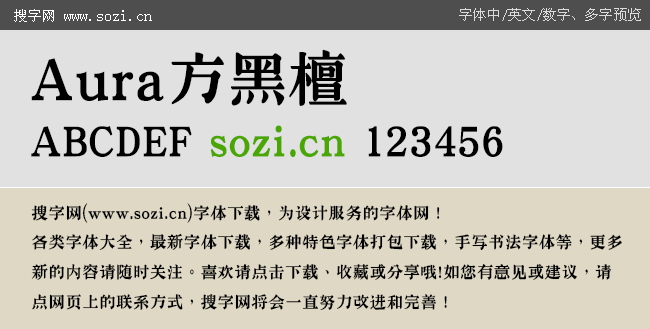
Aura方黑檀字體
搜字網(wǎng)提供一款Aura方黑檀字體中文字體下載,Aura方黑檀字體是一款以宋體為原形設(shè)計的中文藝術(shù)字體,字形端正,簡潔大方,效果非常出色,適合應(yīng)用于廣告設(shè)計、名片設(shè)計、產(chǎn)品設(shè)計等應(yīng)用。